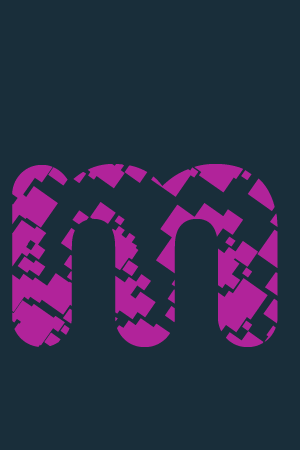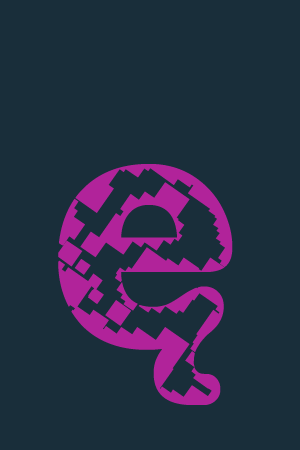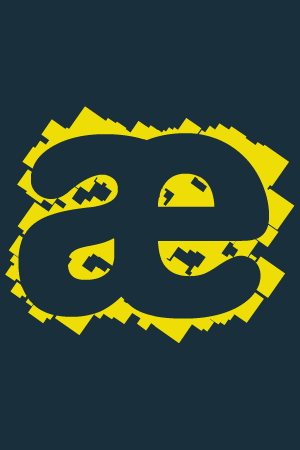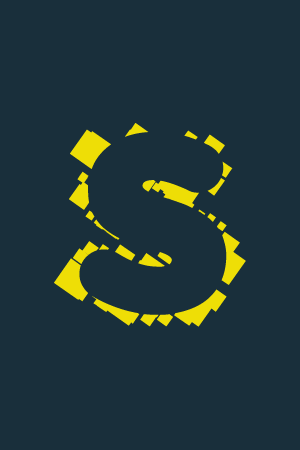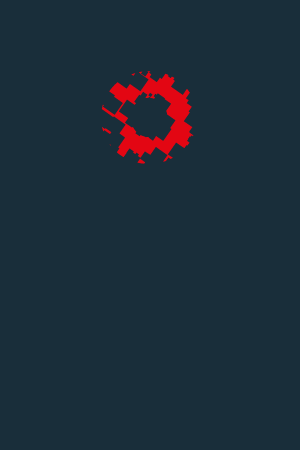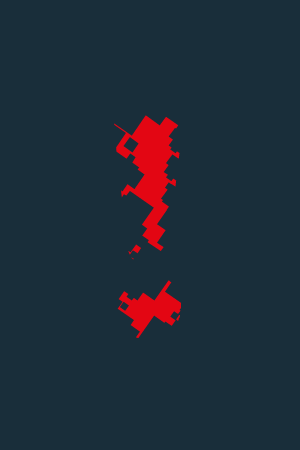
1 año de diseño tipográfico en un video de...
4 minutos de tipografía con S. Grappelli
En este video de 4 minutos hago una recopilación de los glifos de todas las tipografías que he diseñado en el último año, las he animado y he puesto también un poco de ritmo con música de Stéphane Grappelli & Earl Hines, espero que os guste.